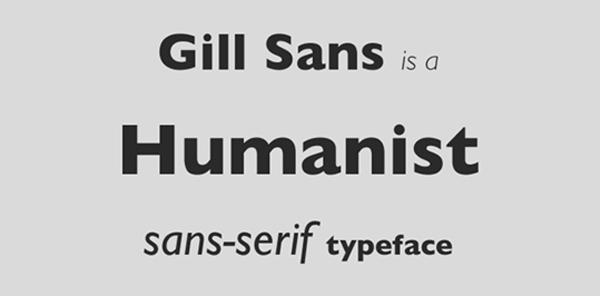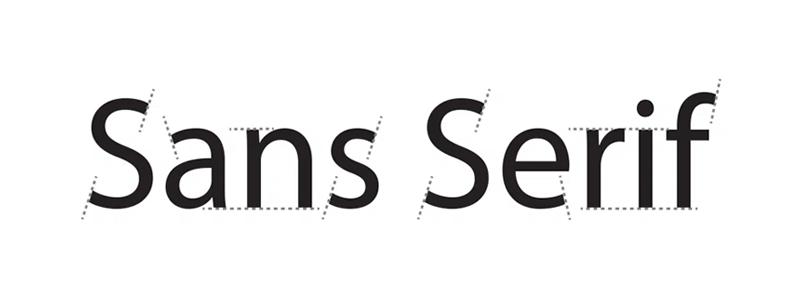
Chắc chắn mỗi Designer đều có cho mình một bộ font chữ yêu thích thường xuyên sử dụng. Tuy nhiên, không phải ai cũng biết đặc điểm của từng loại font chữ và cách dùng chúng trong thiết kế đồ họa. Hãy cùng G-Multimedia tìm hiểu top 5 thể loại font chữ phổ biến và cách áp dụng chúng trong thiết kế nhé!
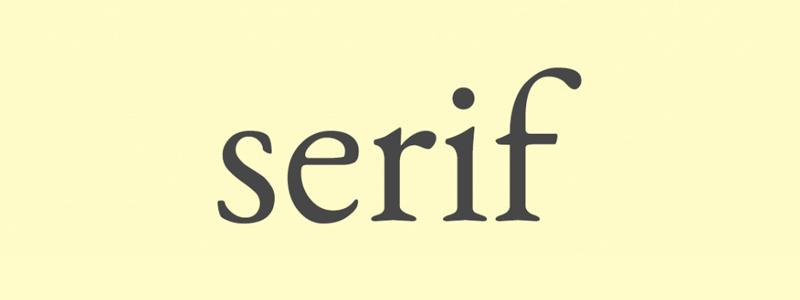
Font chữ Serif, hay có tên gọi gần gũi hơn là “font chữ có chân” là dạng phông chữ lâu đời và cơ bản nhất. Dạng phông chữ cổ điển này được sử dụng một cách rộng rãi và sẽ không bao giờ lỗi thời.
Dấu hiệu nhận biết rõ ràng nhất của dạng font chữ này chính là chúng có “chân” ở trên đỉnh và dưới cùng của từng chữ cái. Tất nhiên, có rất nhiều thể loại phông serif khác nhau, hãy cùng tìm hiểu các dạng font chữ serif phổ biển nhất dưới đây nhé!
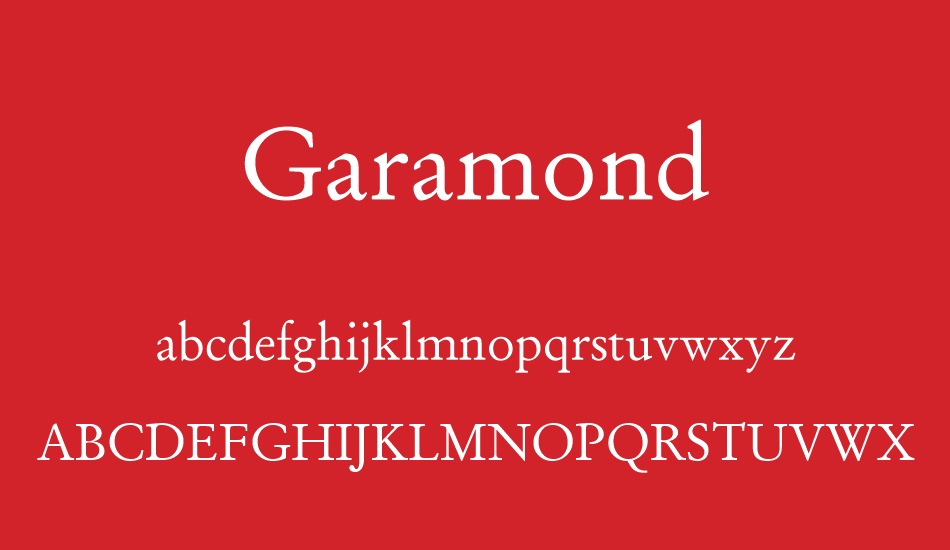
Old style serif (serif cổ điển) là dạng phông chữ phát triển từ thời kì Phục Hưng (Renaissance) vào thế kỉ 15th. Nó được thiết kế dựa trên chữ cổ của người Roman và có đặc điểm là sự tương phản giữa các nét dày và mỏng trong chữ cái cũng như các đường cong nối giữa nét.
Một số dạng phông chữ Old Style Serif phổ biến như: Garamond, Requiem, Bembo, Bookerly, Cartier và nhiều hơn nữa. Ngày nay, dạng font chữ cổ điển này được tìm thấy nhiều trong lĩnh vực in ấn, bìa sách, tạp chí, bài báo và được sử dụng ở dạng body text.
Dạng phông chữ này được giới thiệu rộng rãi lần đầu bởi John Baskerville, một nhà sáng tạo có tiếng ở nước Anh vào giữa thế kỉ 18th. Phong cách của font chữ Trasistional Serif là sự pha lẫn giữa nét cổ điển và một chút đổi mới như sau:
Một số dạng font chữ Transistional Serifs có thể kể tên như Baskerville, Georgia, Bookman, Cambria, Times New Roman,…
Didone là dạng phông chữ Serif hiện đại xuất hiện lần đầu vào cuối thế kỉ 18 và trở thành font chữ tiêu chuẩn cho lĩnh vực in ấn vào thế kỉ 19. Cái tên “Didone” là sự kết hợp giữa hai cái tên của các nhà thiết kế ra dạng chữ này: Firmon Didot và Giambattista Bodoni. Dạng font chữ này đánh dấu sự khác biệt hoàn toàn so với hai dạng phông chữ serif cổ điển kể trên, đặc điểm của font Didone có thể kể đến:
Dạng phông chữ này được sử dụng phổ biến nhất ở các tạp chí thời trang cao cấp bởi sự tinh tế, hiện đại, sang trọng mà chúng mang lại. Một số font chữ phổ biến dạng Didone có thể kể đến là: Bodoni, Didot.
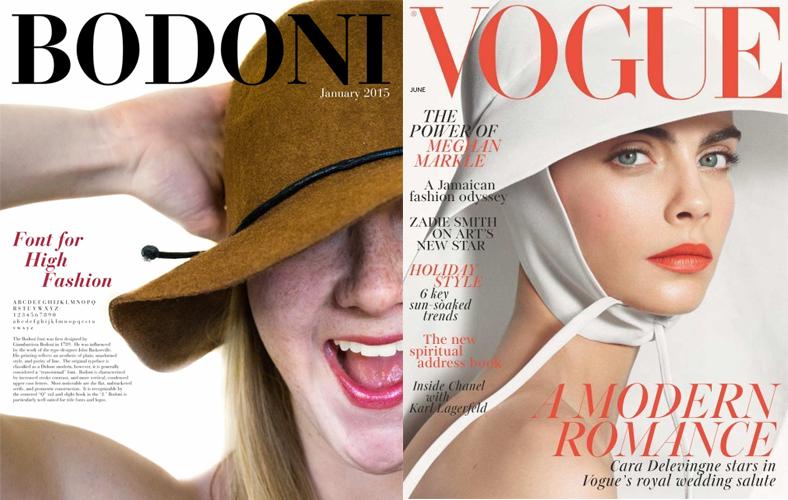
Dạng font chữ Slab Serif ra đời vào đầu thế kỉ 19, với mục đích chính là tạo sự thu hút mạnh mẽ với người đọc. Điều này cũng dễ hiểu bởi các chữ cái của Slab Serif có đường nét rất dày, chứ không còn tương phản như các font kể trên.
Đây cũng có thể coi là dạng phông chữ serif hiện đại, với sự gọn gàng và táo bạo của chúng, Slab serif được áp dụng rất nhiều vào lĩnh vực thiết kế đồ họa, ví dụ như thiết kế tạp chí, logo, thiết kế web, tạp chí,…
Một số font chữ Slab serif có thể kế tới như: Rockwell, Bogart, Bondie, FF Unit Slab,….
Font Serif thể hiện toát lên sự chuyên nghiệp, cổ điển và đáng tin cậy. Vì vậy, bạn có thể sử dụng cho các thiết kế liên quan tới tập đoàn, công ty hoặc doanh nghiệp.
Bên cạnh đó, Serif cũng đem tới sự tinh tế, sang trọng nên hoàn toàn có thể sử dụng để làm nổi bật phần tiêu đề của bạn. Bạn có thể tham khảo các font chữ Slab Serif để hiểu hơn.
Dạng phông chữ này có cái tên khá hay ho, với từ “Sans” dịch từ tiếng Pháp ra có nghĩa là “không có”. Còn Serif như chúng ta đã nói ở trên là dạng chữ có "chân”. Vì vậy, Sans serif có thể coi là phông chữ “không có chân”. Nghe khá ngộ nghĩnh phải không? Nhưng tính chất của nó đúng là như vậy, hãy cùng tìm hiểu các dạng Sans serif phổ biến trong phần dưới đây nhé!
Từ “Grotesque” khi dịch ra tiếng việt có nghĩa là “kỳ cục, kì quái”. Vì sao người ta lại đặt tên cho phông chữ là kì quái? Chẳng lẽ nó lại ghê sợ và xấu xí đến thế. Thật ra, chúng là dạng font chữ khá bình thường nhưng do ảnh hưởng bởi hoàn cảnh ra đời nên bị coi là “khác biệt”.
Như đã nói ở trên, Serif (có chân) là dạng phông chữ đã xuất hiện trong hàng thế kỉ, vì vậy khi đột nhiên xuất hiện một loại phông chữ “không chân”, chắc chắn sẽ khiến người đọc không khỏi khó chịu và nghĩ rằng chúng thật xấu xí, kì quặc.
Cũng dễ hiểu bởi điểm chung của dạng font chữ Serif là chúng rất tinh tế và sang trọng, còn Sans serif thì lại là sự mạnh mẽ và vững chãi. Từ “Grotesque” bắt đầu được gán cho dạng phông chữ này kể từ khi một nhà sáng tạo người Anh, William Thorowgood thiết kế phông chữ Seven Line Grotesque vào năm 1832.
Đặc điểm của dạng phông chữ này là đường nét của chúng chúng có ít sự tương phản và khá bằng phẳng. Thời điểm mới ra mắt, dạng font này chưa có nhiều biến thể nên chỉ sử dụng được cho phần Main heading mà thôi.
Neo-Grotesque Sans Serif là dạng font hiện đại hơn, đời mới hơn phông chữ kể trên. Điểm khác biệt đó là dạng Neo-Grotesque sans serif có phần đơn giản và giản dị hơn. Dạng phông chữ này xuất hiện lần đầu vào khoảng năm 1950, đây cũng là thời điểm font chữ Helvetical ra đời - một trong những phông chữ nổi tiếng nhất thế kỉ 20.
Sans Serif mang tới sự hiện đại và đa dạng hơn và Sans serif cũng thể hiện sự thân thiện và gần gũi hơn với người đọc. Vì vậy, bạn có thể sử dụng dạng phông chữ này ở mọi thể loại thiết kế.